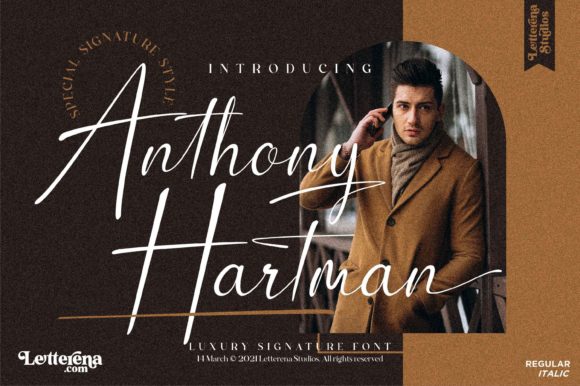
Энтони Хартман - красивый и изысканный шрифт.
Он имеет стильный, элегантный и современный вид, который может быть использован для логотипов, брендинга, приглашений, канцелярских принадлежностей, свадебных конструкций, сообщений в социальных сетях, и многое другое!